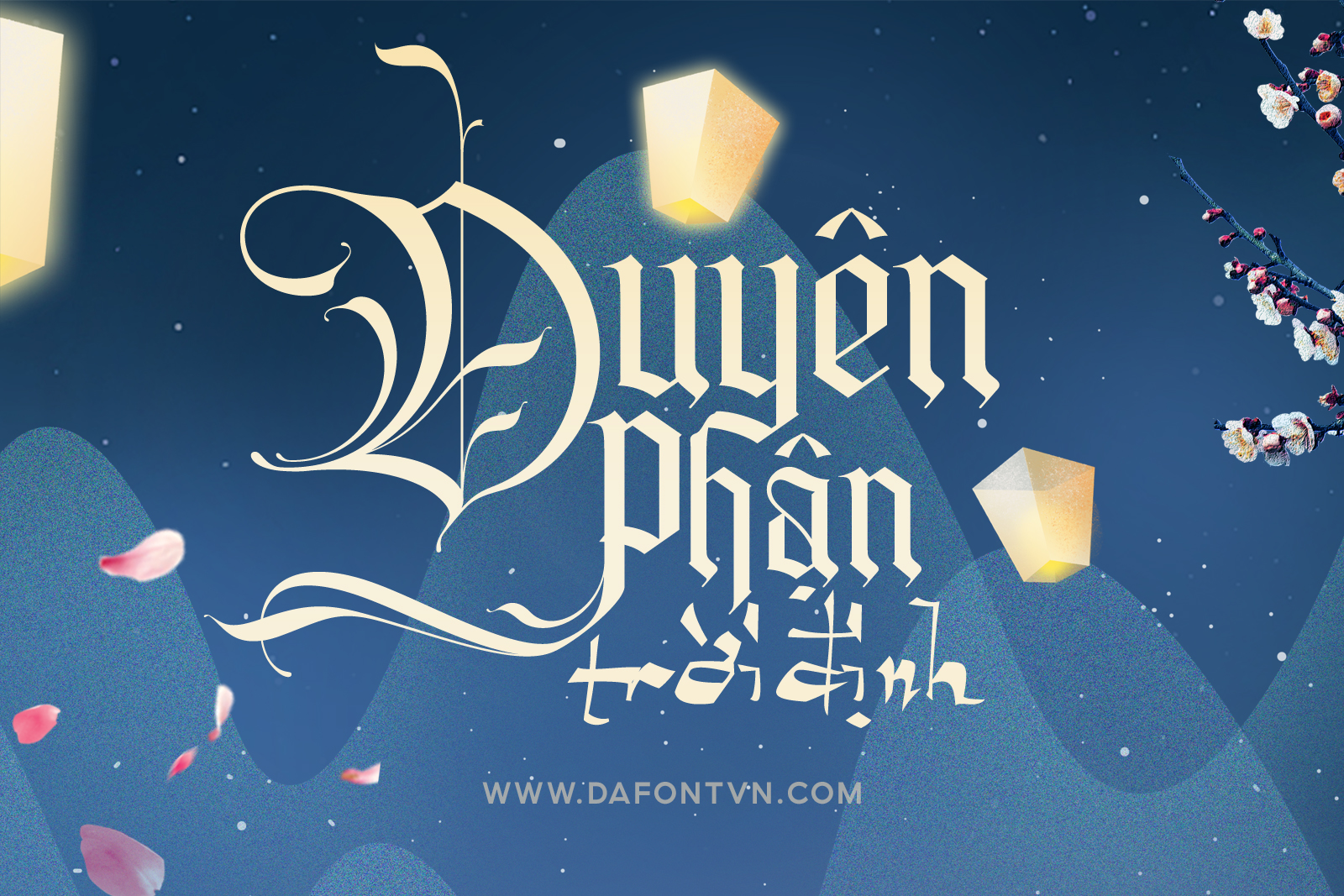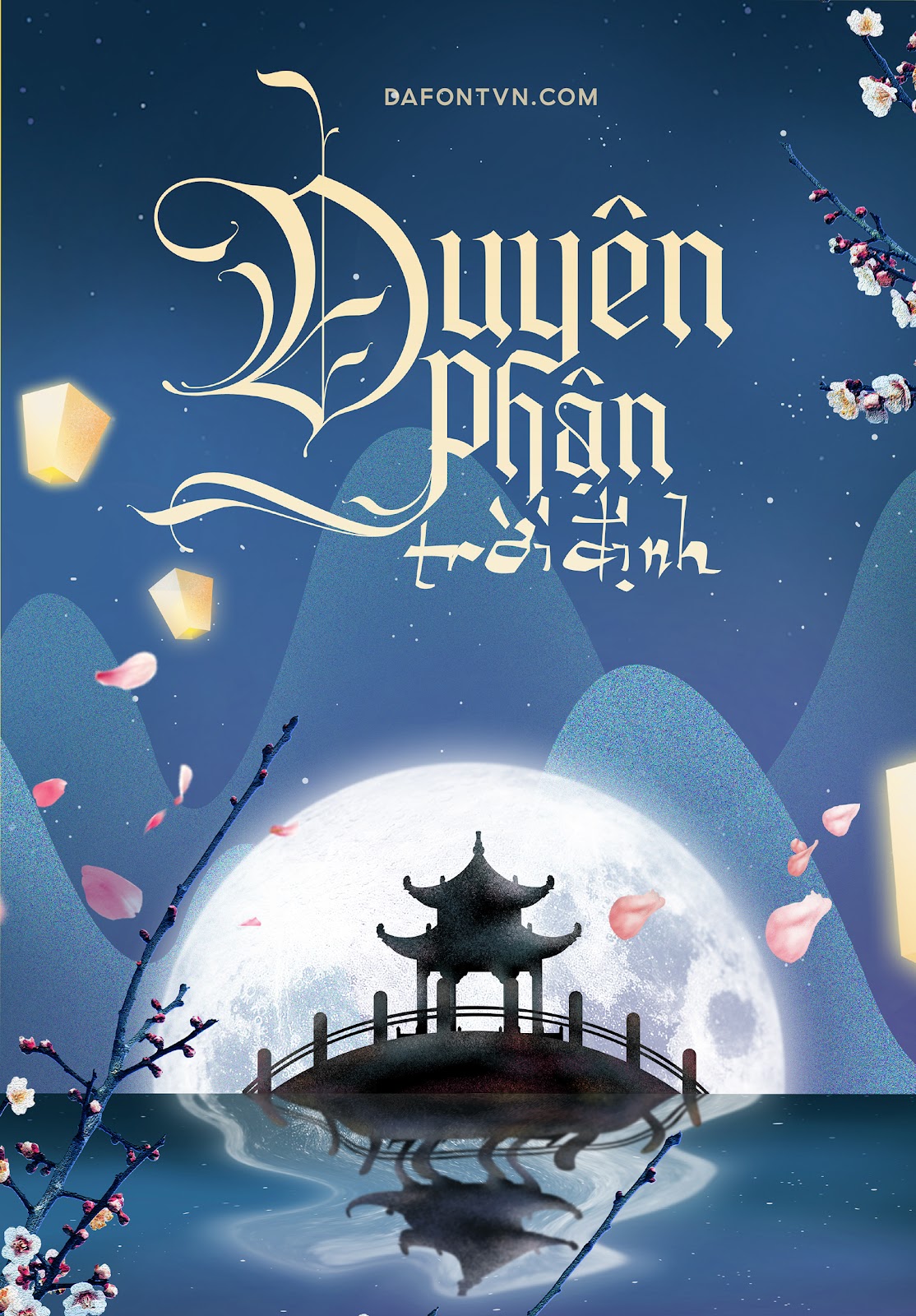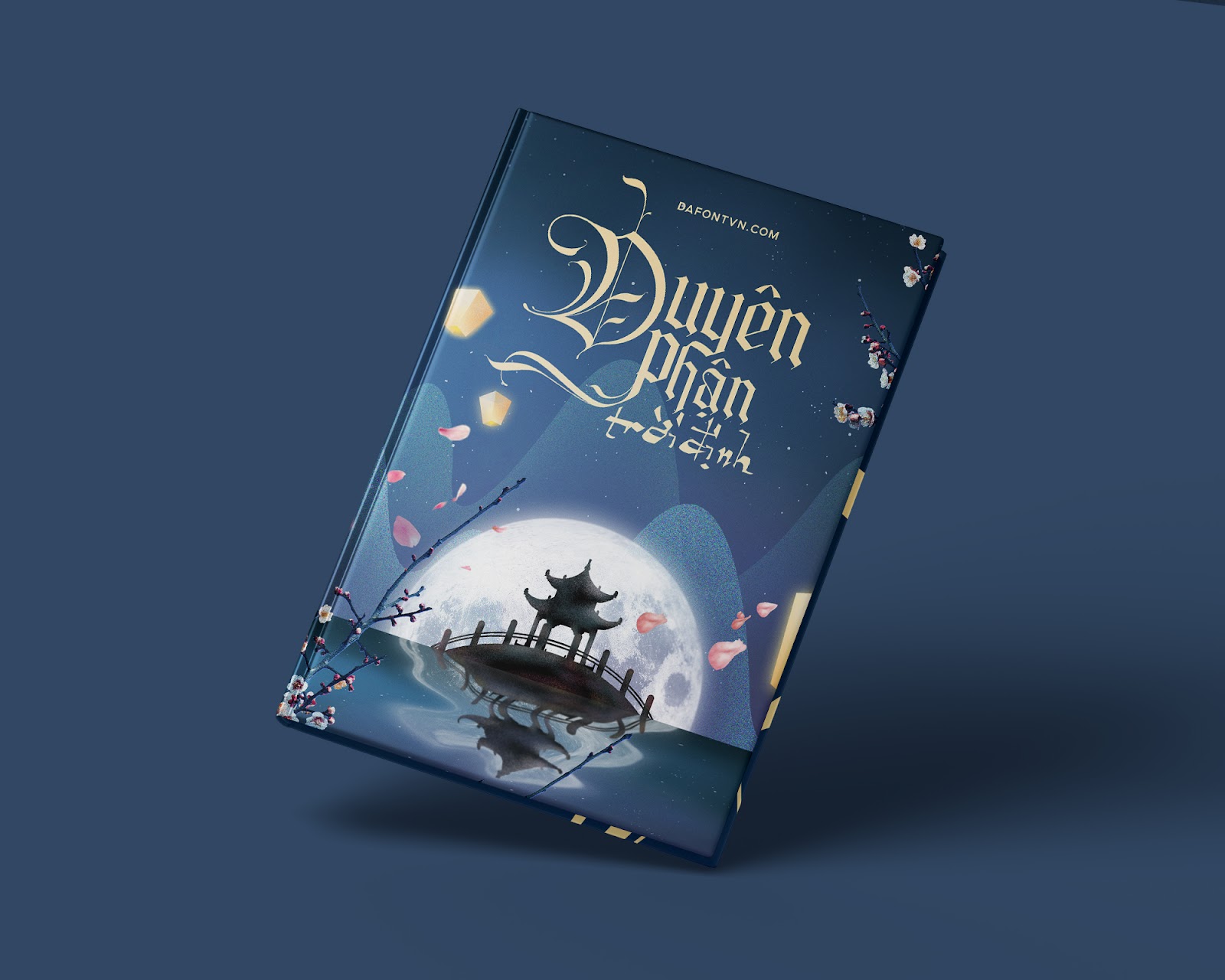
Font việt hóa Belligoes – Kiểu font Gothic rất đẹp
Belligoes là một kiểu font lấy cảm hứng từ các thiết kế Gothic hệ thống chữ viết được sử dụng khắp Tây Âu. Các dạng chữ được tạo nên với một loại bút sắc rộng nhưng nhấn mạnh các điểm chuyển tiếp giữa các nét văn bản.
Font Belligoes đi kèm với các ký tự thay thế độc đáo để bạn có thể tạo ra các tác phẩm ấn tượng hơn.
Font Belligoes rất phù hợp để sử dụng trong việc tạo các thiết kế mang hơi hướng gothic, thiết kế bìa truyện, tạp chí, hình xăm, bao bì, nhãn hàng… hoặc bất kỳ thiết kế nào cần sự mạnh mẽ mang một chút Blackletter.